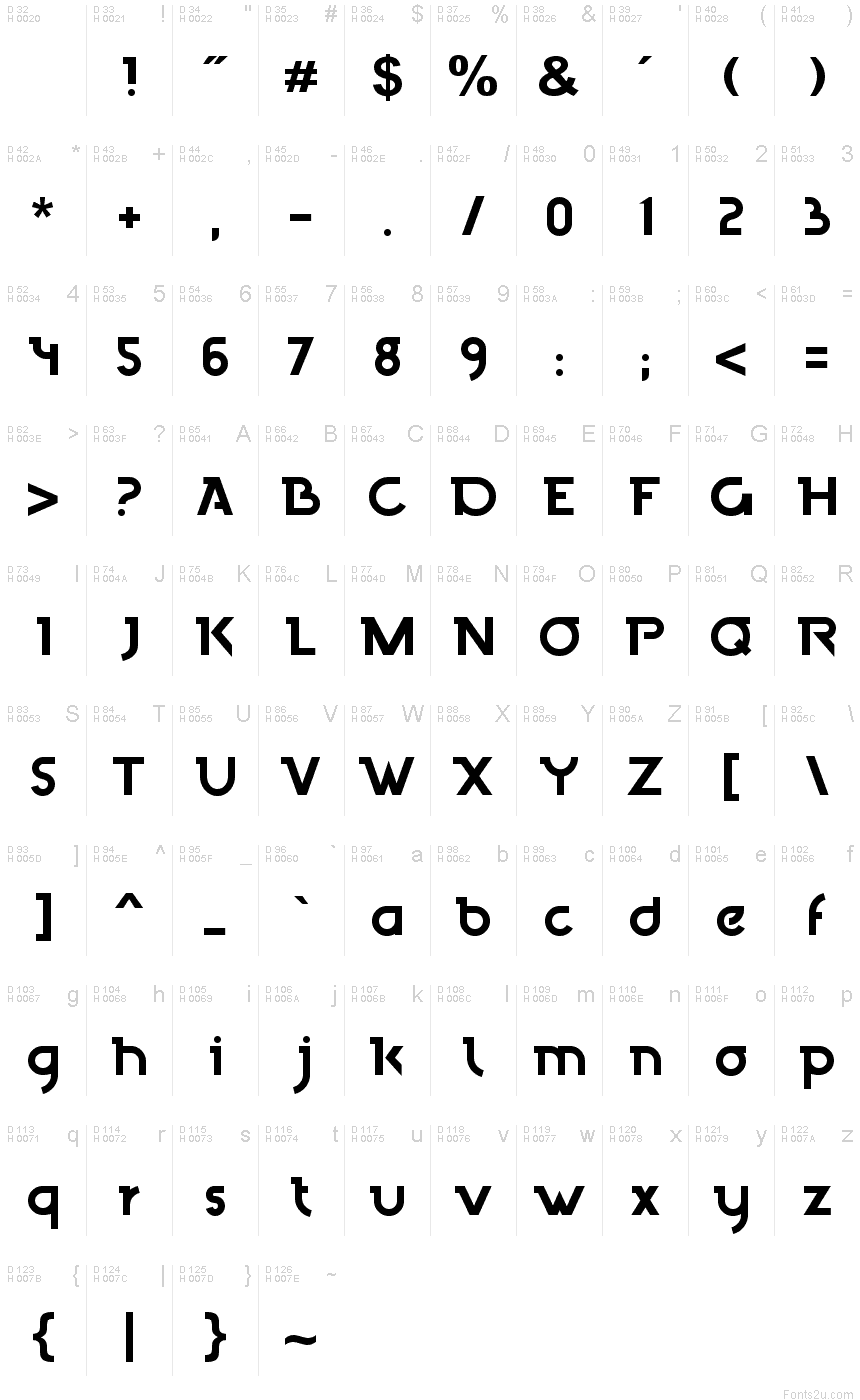
Finchley od Levi to geometryczny krój bezszeryfowy z odważnym, modułowym zacięciem. Grube, równe kreski, kwadratowe wykończenia i idealnie okrągłe brzuszki liter nadają jej wyrazistą, niemal zabawkową formę, podczas gdy detale takie jak oddzielona kropka i przycięte łuki dodają jej technicznego, eksperymentalnego charakteru. Jest solidna, a zarazem figlarna – wygląda, jakby litery zbudowano z błyszczących plastikowych klocków.
Ten darmowy font świetnie sprawdza się w logotypach, futurystycznych plakatach, opakowaniach, oznakowaniach, okładkach albumów i mocnych nagłówkach stron internetowych, gdzie potrzebujesz silnego, zapadającego w pamięć napisu. Użyj Finchley w większym rozmiarze, aby jej ostra geometria i nietuzinkowy rytm naprawdę wybrzmiały; w tekstach głównych połącz ją z prostym, neutralnym krojem bezszeryfowym, aby zachować przejrzystość i czytelność projektu.